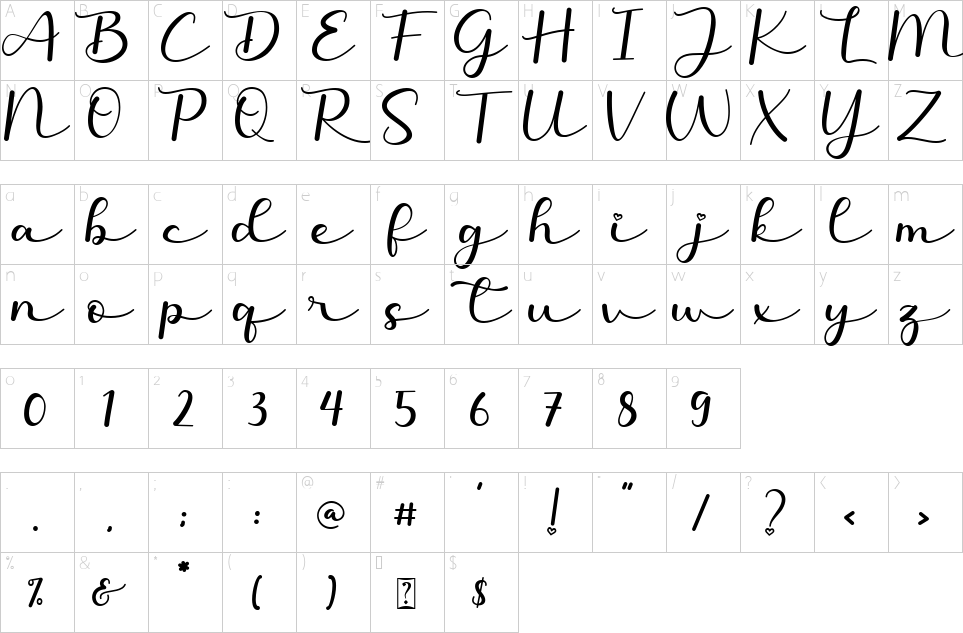
Miatta Font | 1001 Free Fonts – Fonte Grátis
Descubra Miatta, uma fonte de linhas leves e elegantes. Desenvolvida pela AEN Creative Studio, Miatta é perfeita para projetos que exigem um toque suave e sofisticado. Suavemente fluida e suave, esta fonte é ideal para textos legíveis e atraentes, seja em design editorial, publicações digitais ou até mesmo para criações gráficas digitais. Com um design minimalista, Miatta oferece uma versatilidade ótima para diversos formatos e tamanhos de texto. Recentemente baixada 2.928 vezes, é uma escolha perfeita para aqueles buscando uma fonte única e versátil. Baixe Miatta e adicione profundidade e estilo a suas criações.